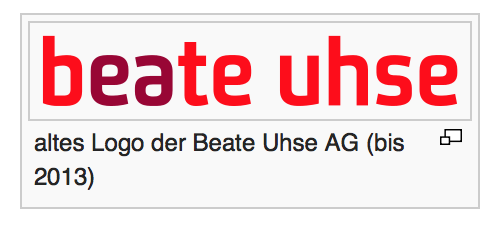
Schrift wo sich das "a" und "e" sehr ähnlich, wenn nicht gleich sind
Suche eine Schrift wo sich das "a" und "e" sehr ähnlich, wenn nicht gleich sind.
Ja perfekt, genau in diese Richtung! Danke schon mal!
Wie heißt die Schrift denn? Oder die Basis?
Kann es Tasse von Font Bureau sein?
Ich weiß nicht, ob eine Satzschrift für dieses Logo als Ausgangsbasis diente, aber das Logo wurde bei Enterprise IG (heute: The Brand Union) entwickelt. So wie ich die Kollegen kenne, die damals mit dem Logoentwurf befasst waren, würde ich vermuten, dass die Schrift auf alle Fälle modifiziert, wenn nicht gar neu gezeichnet wurde.
Guck dir mal die Liste der Spornlosen an – wahrscheinlich wird da am ehesten was bei sein, oder?!  :tuschel:  :-?
Man könnte auch mal Fonts wie Joost, Regis Sans oder Ladislav ansehen und probieren deren a für das e zu nutzen – oder umgekehrt das e für ein a bei der Verwendung von Ivan Reschniev, Fidel oder ähnlichen.
Das ist korrekt, da war Hubert Jocham am Werk … (ist nicht mehr in seinem aktuellen Portfolio, sozusagen eine Jugendsünde? Schon komisch, daß bei dem Logo mit dem gewissen Bildwitz, der durch die Drehung der sehr ähnlichen, wenn nicht identischen e und a entsteht eine »spornlose« zum Einsatz kam, ähem)